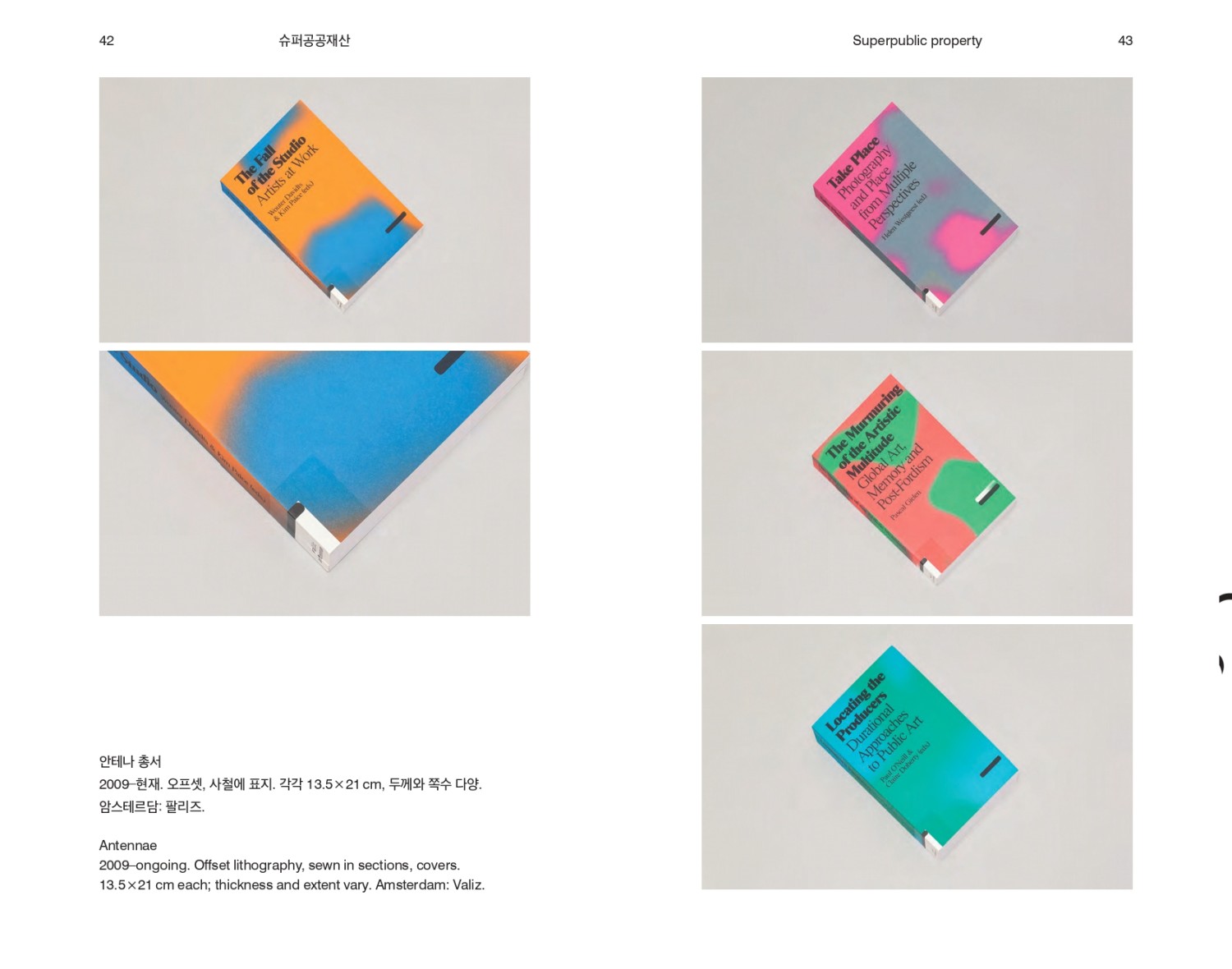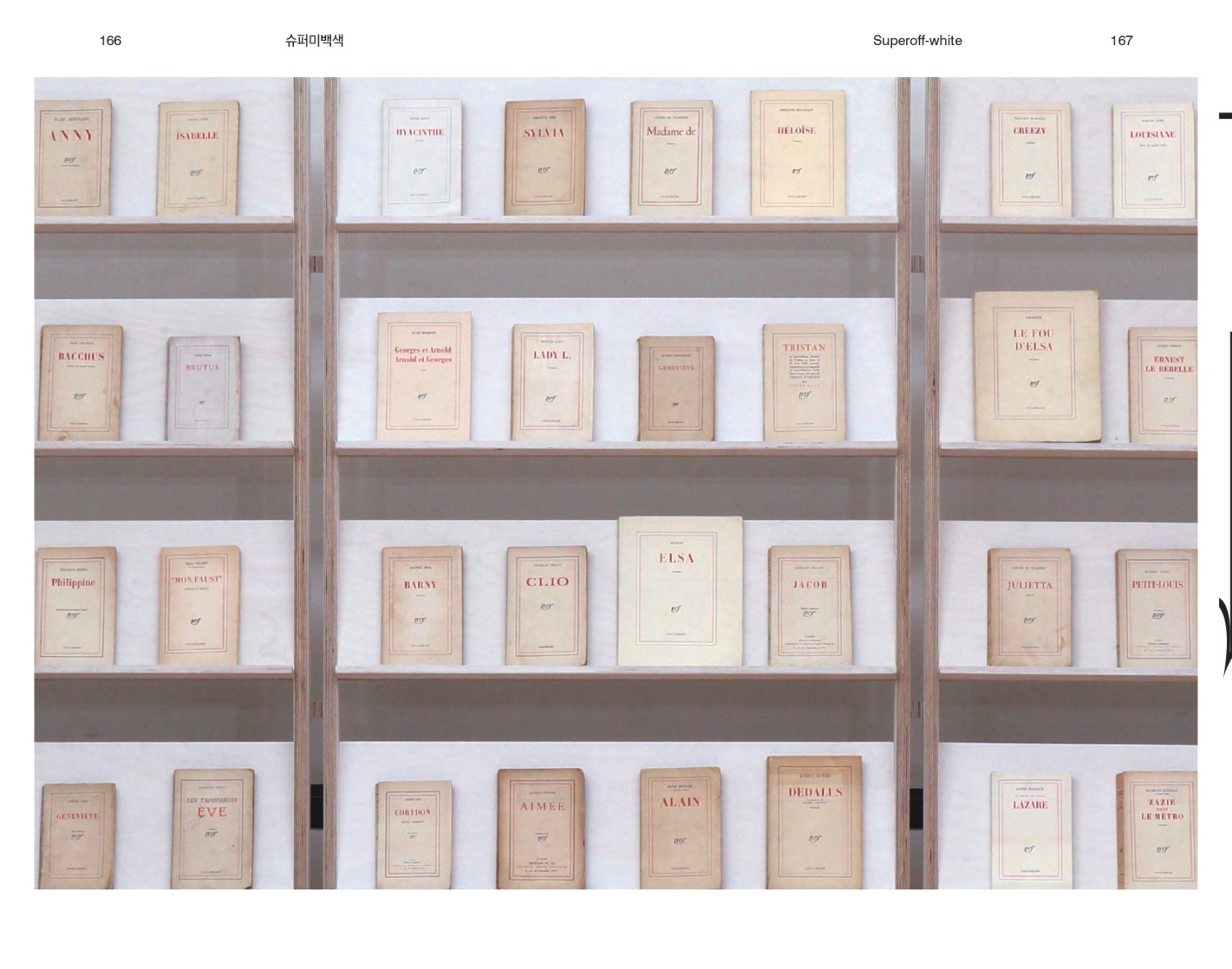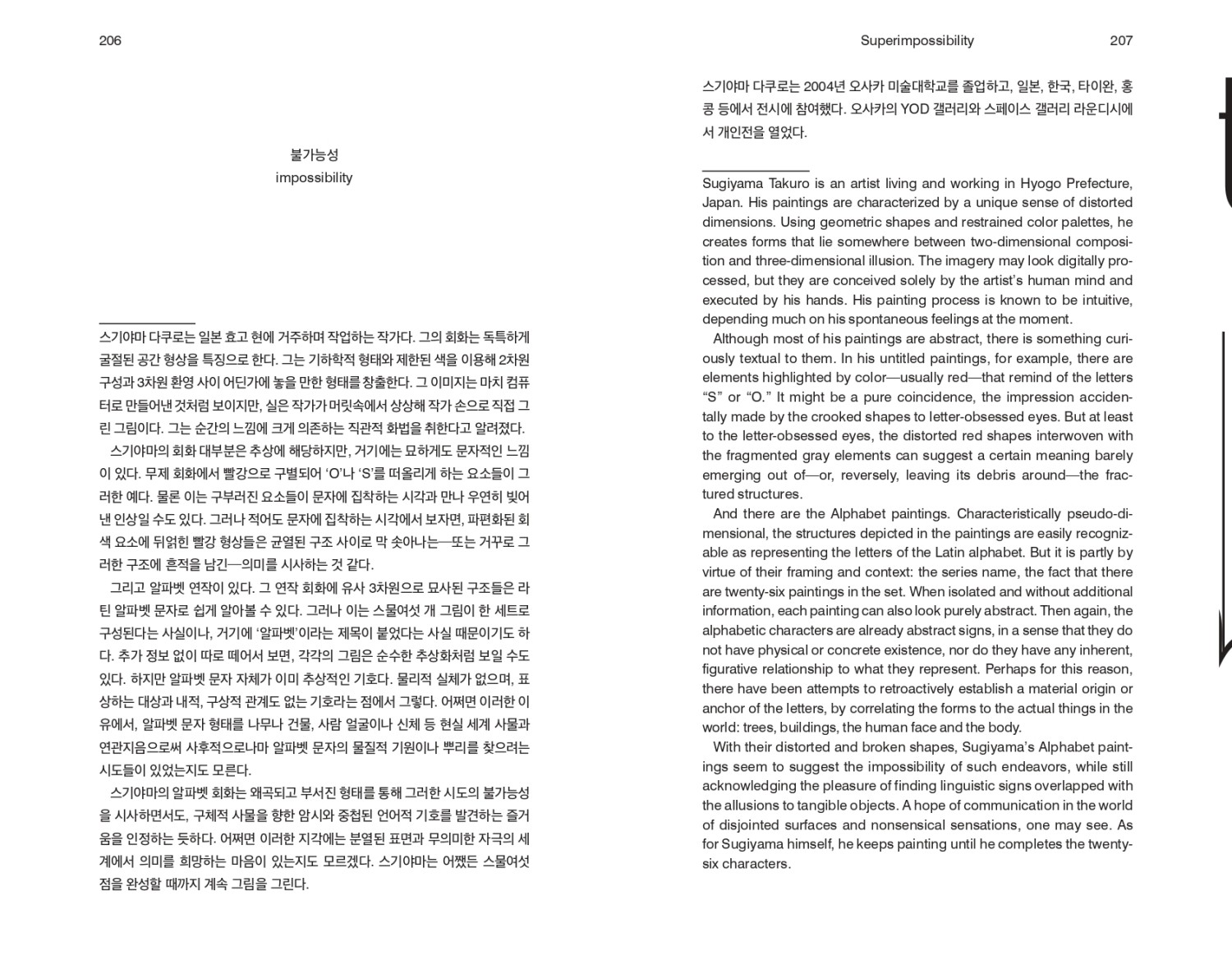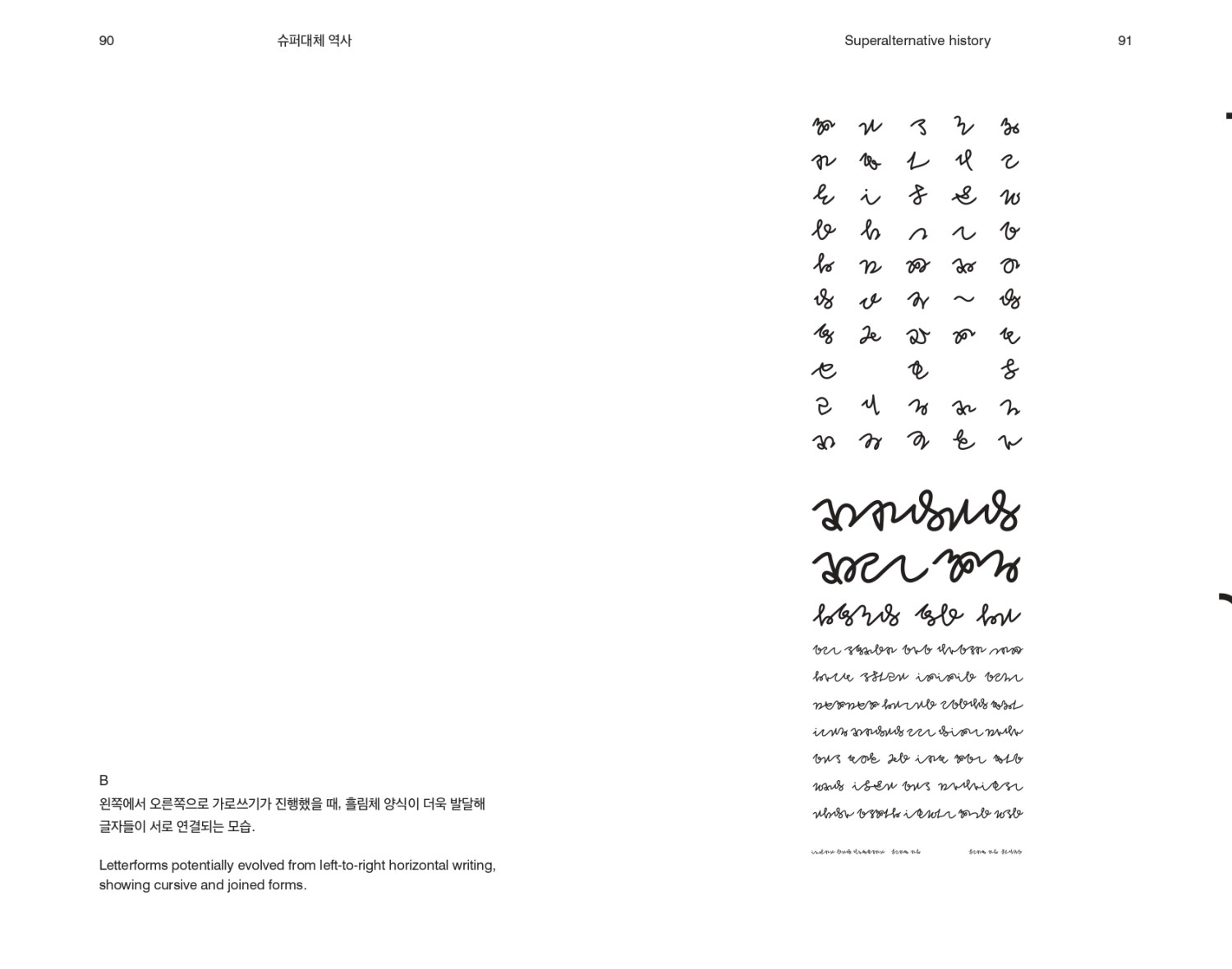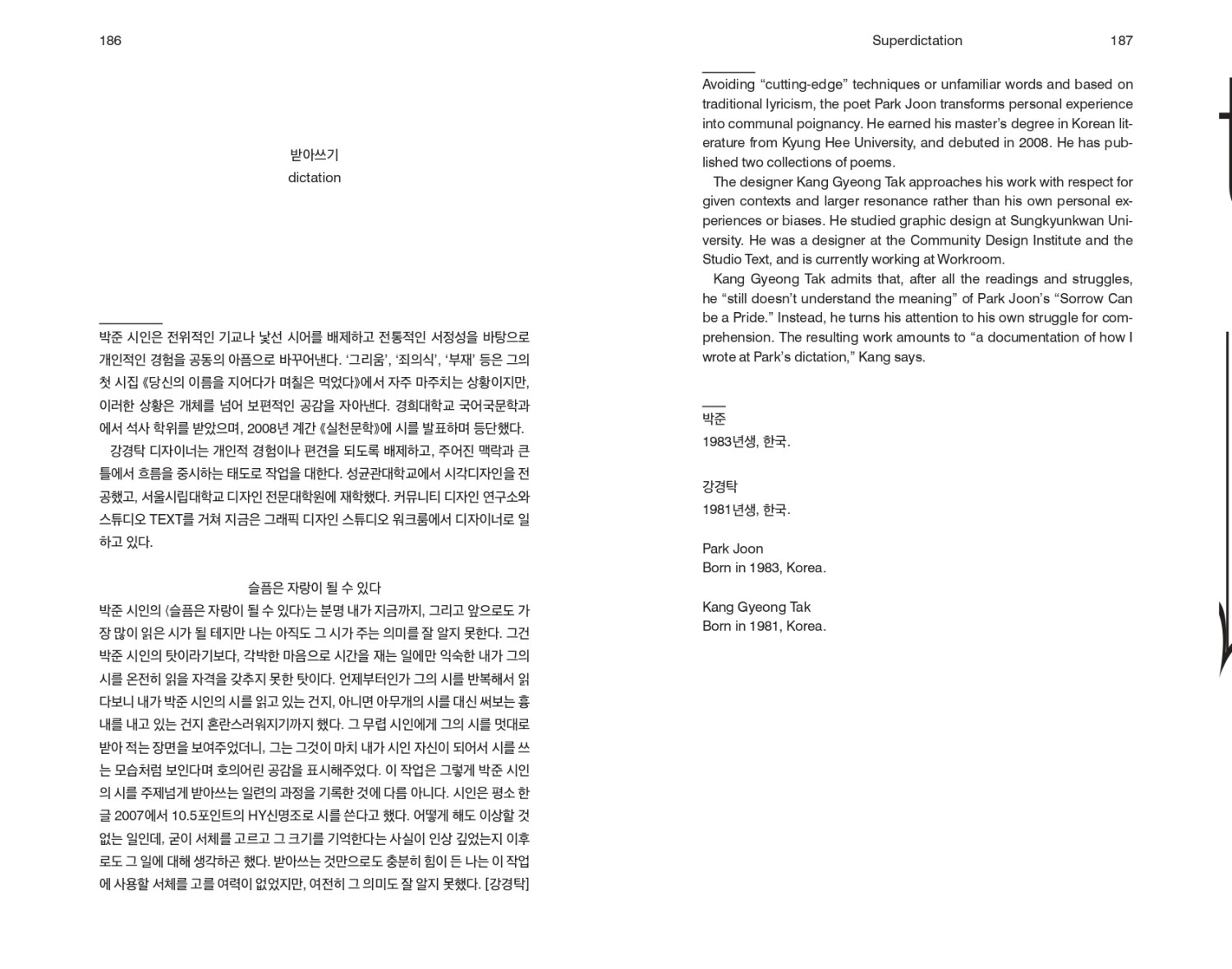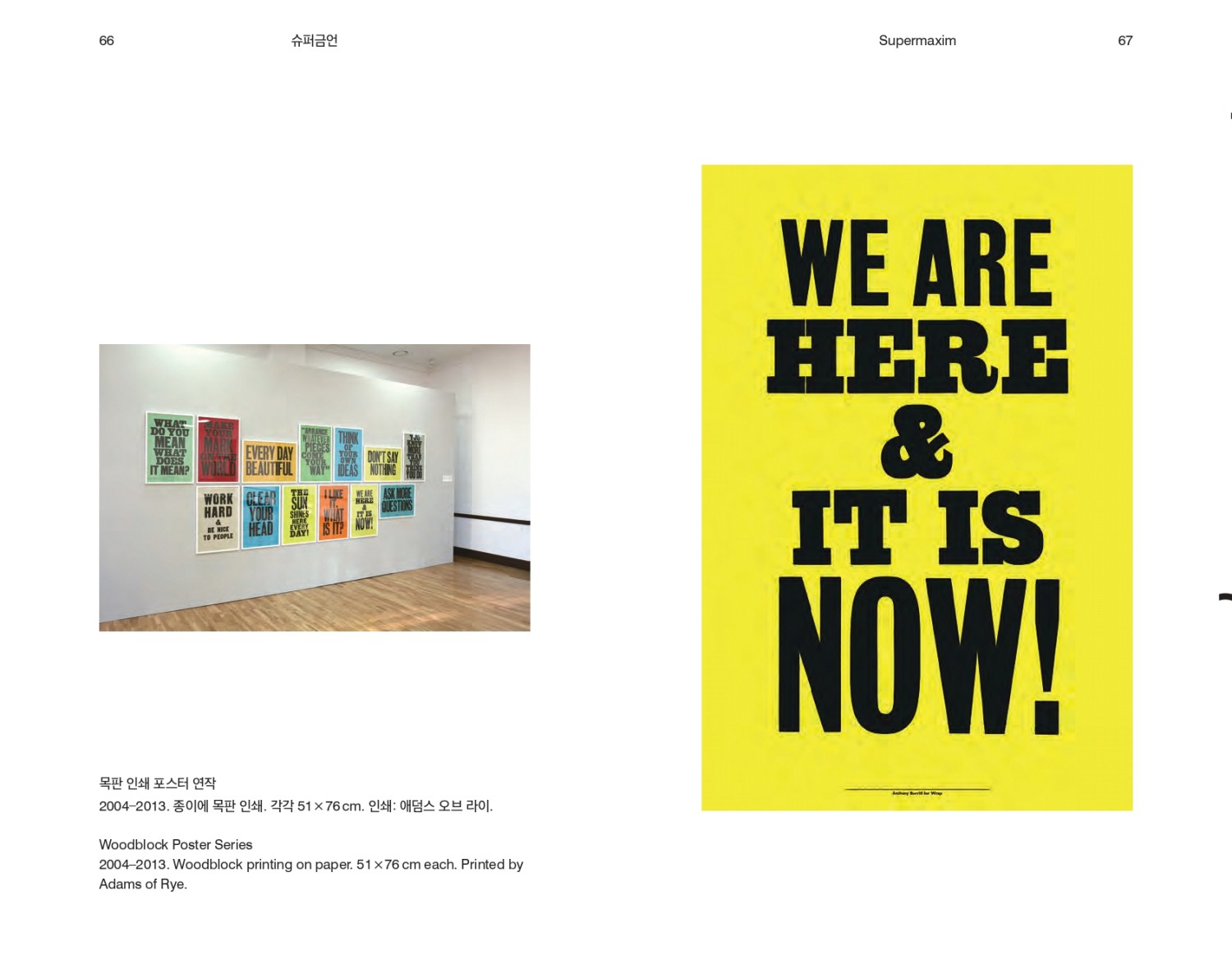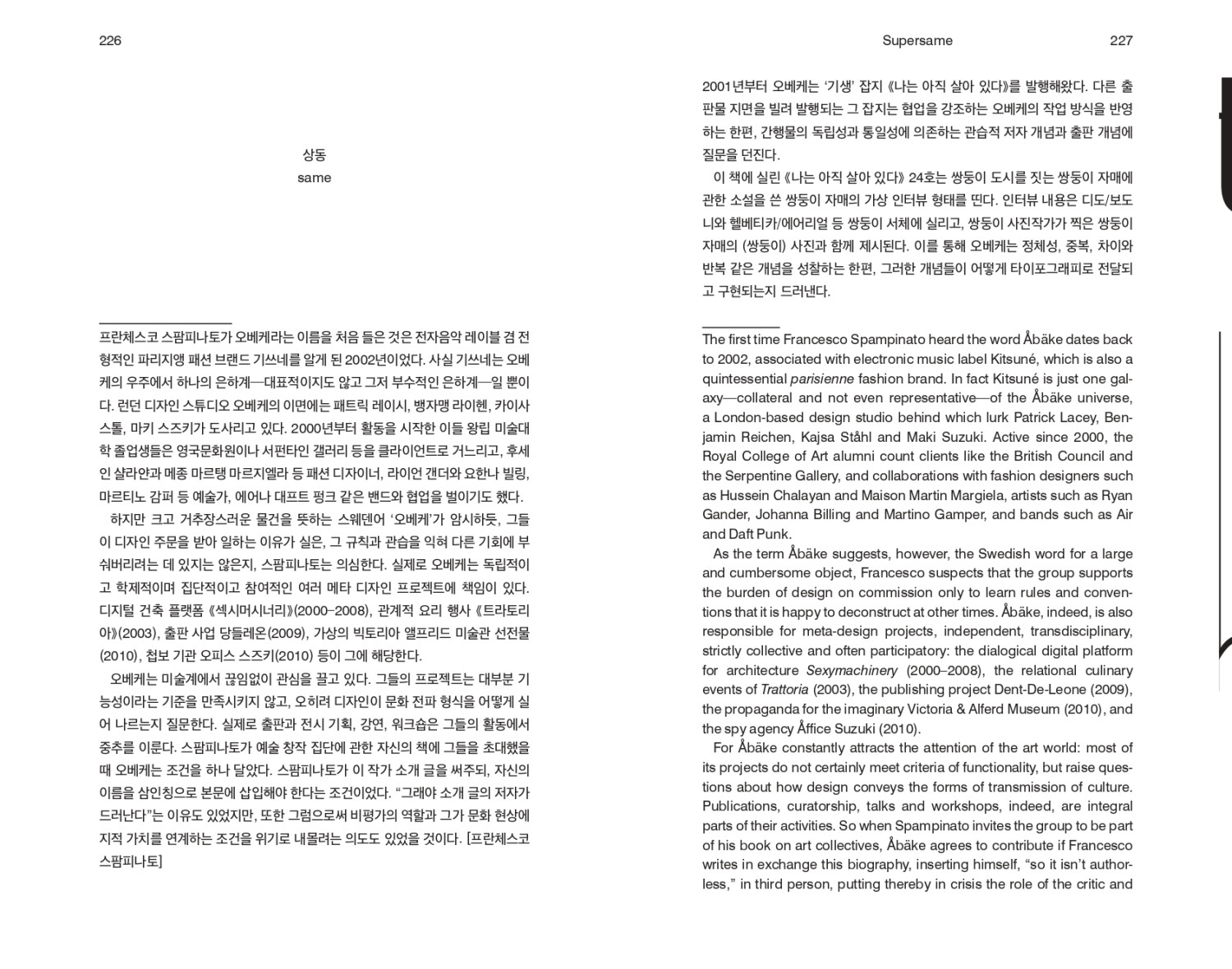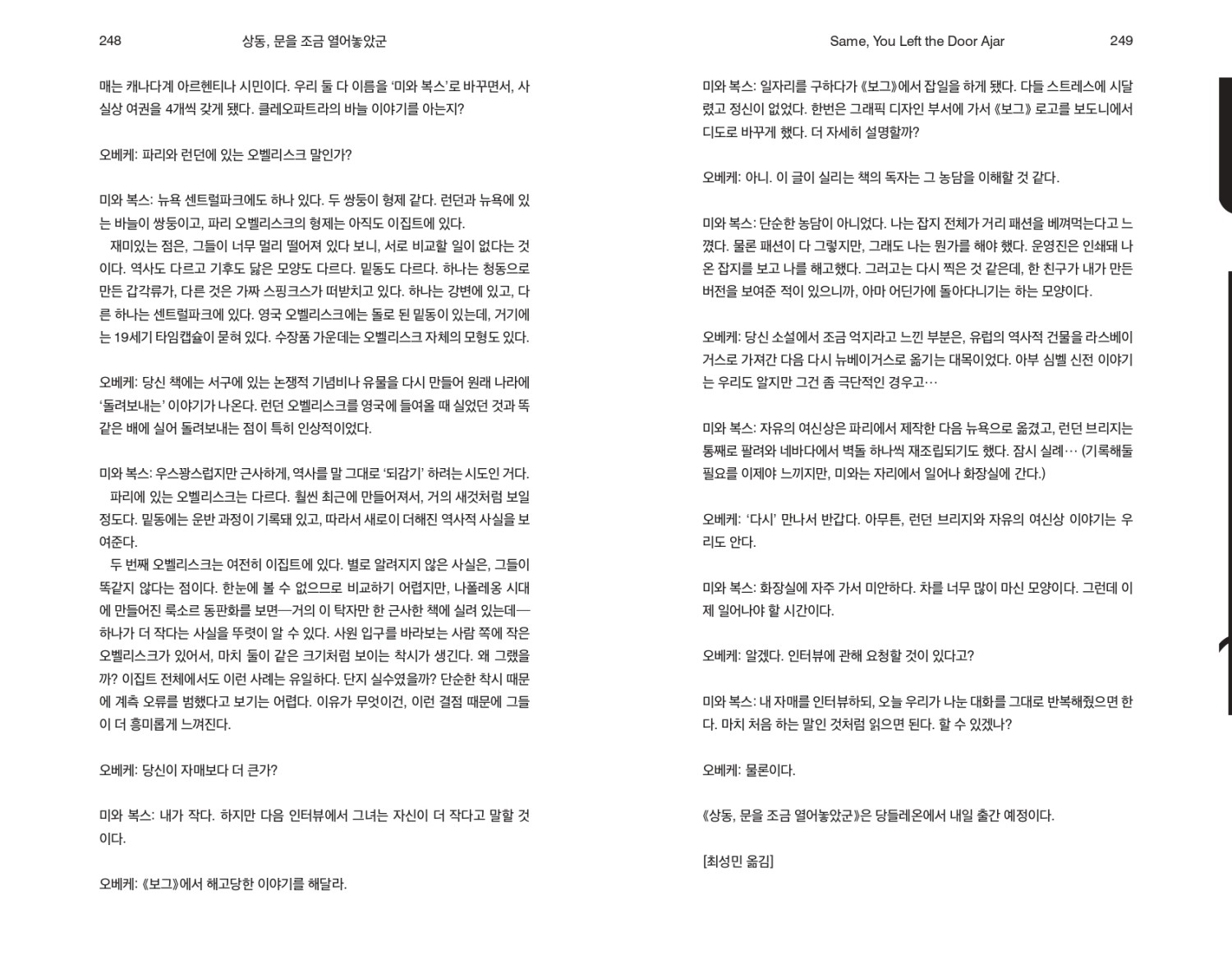
타이포잔치 2013: 슈퍼텍스트
- 문자와 문학
- 문화역서울 284 전관
- 2013년 8월 30일 – 2013년 10월 11일
문자와 문학. 타이포잔치의 세 번째 주제는 이 단순하면서도 무한한 조합으로부터 출발했다. 《슈퍼텍스트》는 문자의 형상뿐 아니라 그 안에 깃든 이야기, 언어, 문화의 층위를 탐색한 실험장이었다. 문화역서울 284 전관에서 열린 이번 전시는 본전시를 중심으로 리서치 프로젝트, 연계 전시, 워크숍, 강연, 한글날 전야제 등 풍부한 프로그램을 통해 타이포그래피를 언어적 사건으로 확장했다. 활자는 단지 눈에 보이는 것이 아니라, 몸으로 겪고 귀로 듣고 기억으로 이어지는 것임을 보여준 시도였다. 총감독 최성민의 기획 아래, 전 세계 57팀의 참여자들이 타이포그래피를 통해 문학과 사회, 역사와 기술, 일상과 실험 사이의 접속을 제안했다. 33,000여 명의 관람객은 이 전시를 통해 활자를 읽는 것이 아니라 살아보는 일이 될 수 있음을 경험했다. 《슈퍼텍스트》는 타이포잔치가 비로소 ‘문자와 ○○’이라는 주제로 사회문화적 상상력을 불러들이기 시작한 전환점이었다. 동시에 타이포그래피 비엔날레로서의 내실을 다지고, 국제적 위상을 공고히 하는 계기가 되었다. 이후의 타이포잔치들이 지속적으로 실험하고 확장해나가게 될 ‘문자적 사유의 장’, 그 첫 페이지가 이 전시에서 펼쳐졌다.